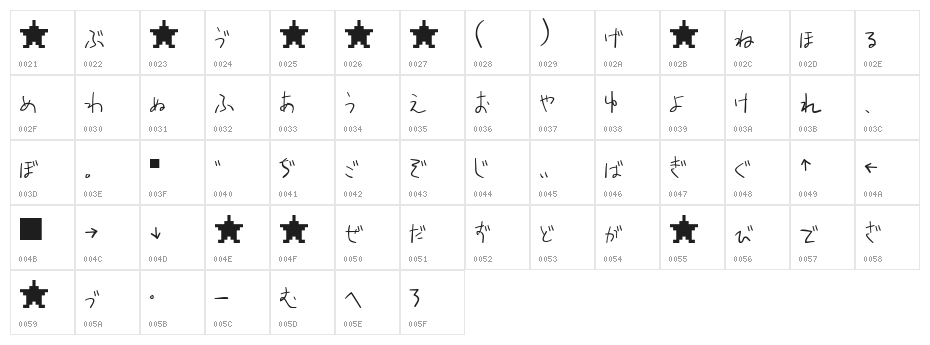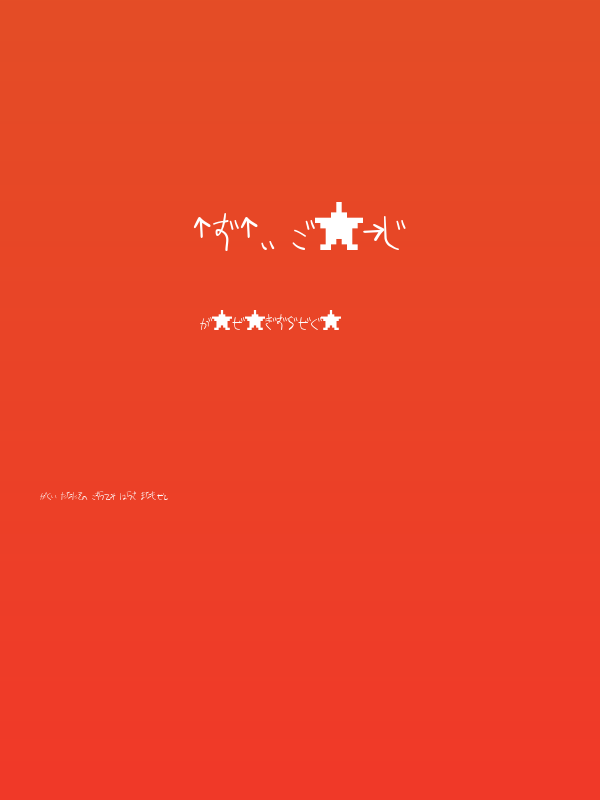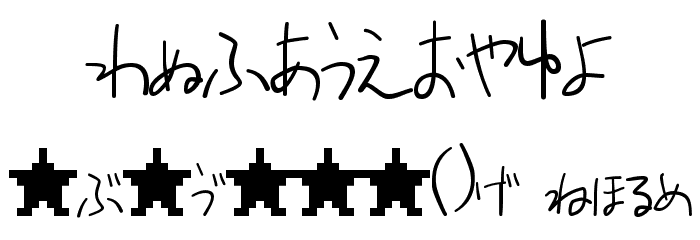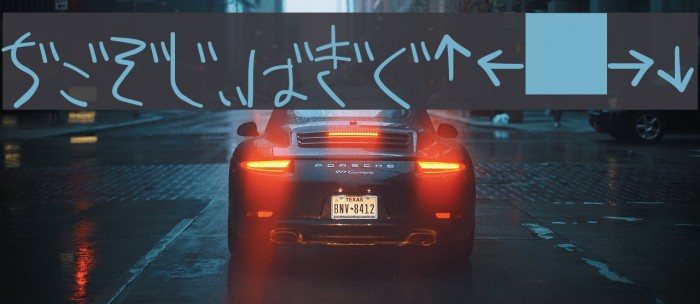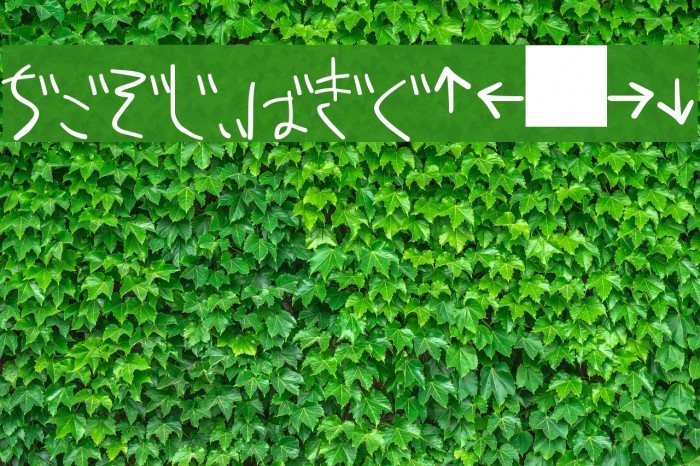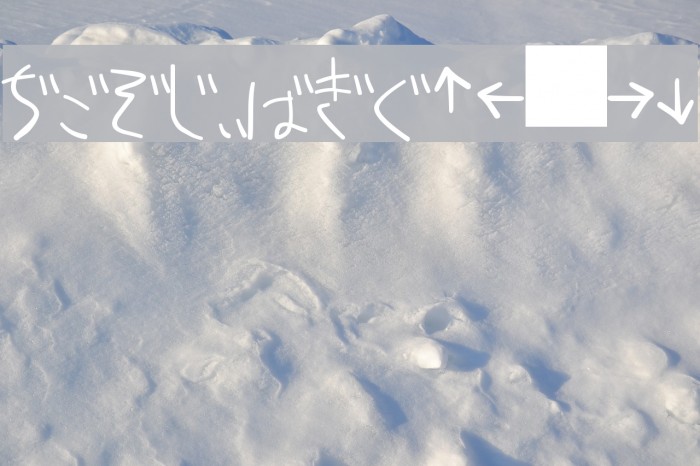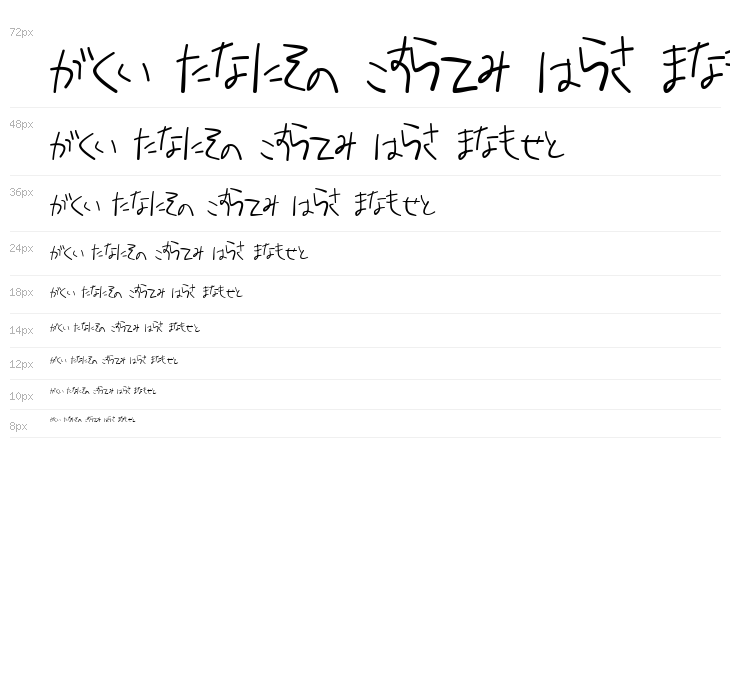
irie Bold Font
| Stile generale | Modern, Casual |
| Caso d'uso | Headlines, Personal notes, Casual invitations |
| Progetti proposti | Ideal for personal notes, casual invitations, creative projects, and any design requiring a friendly touch. |